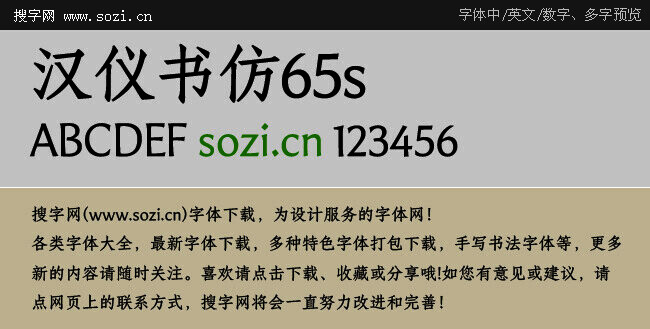
汉仪书仿65s
搜字网给大家提供一款汉仪书仿65s中文字体下载,汉仪书仿是一套针对正文排版使用的仿宋字体,由细到粗共5款字重。汉仪书仿家族的创作初衷是为了打破仿宋体现代应用之困境,其结构端稳严谨,字形呈方形,相较于仿宋体中宫略微放松、重心略低,倾斜角度较平缓,楷化的笔画带来了柔和的手写感而削弱了尖锐硬朗的刀刻感。与常规的仿宋体相比,这套字体具有更好的易读性。适用于画册设计、海报设计、包装设计等场合使用。(本字体为个人非商用版,如需要商用请联系汉仪公司购买版权)